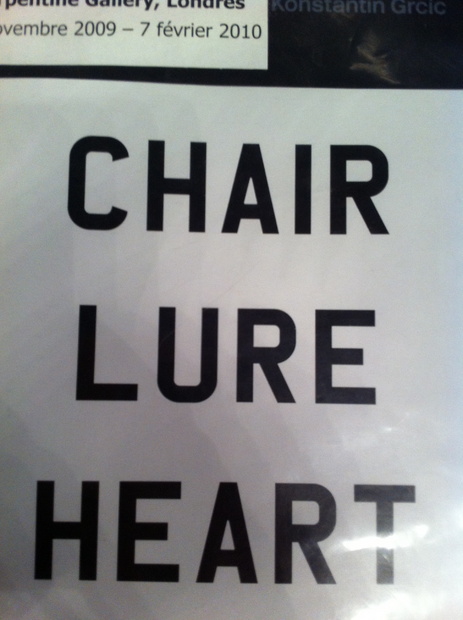
kann mir jemand sagen wie diese schrift heißt?
kann mir jemand sagen wie diese schrift heißt und sagen, wo ich sie herbekomme?
habe sie in einem katalog von konstantin grcic gesehen und würde sie dringend für einen flyer brauchen.
Tja, was die Formensprache angeht, erinnert diese Schrift an die Bank Gothic, sie ist aber wesentlich schmaler. Morgen früh sind bestimmt ein paar mehr Kollegen wach, die das genauer eingrenzen können. :-)
Haben wir die nicht schon mal gesucht … ?
"Mandatory" von K-Type ist es.